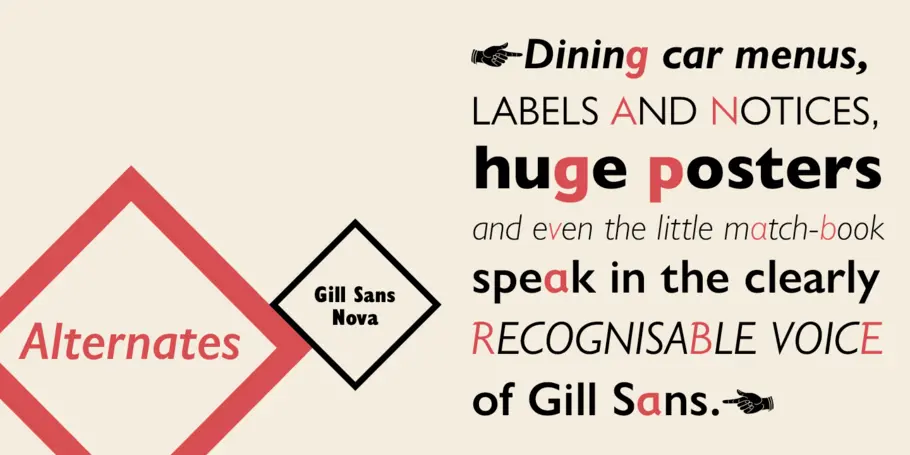
Gill Sans Nova®
La serie Eric Gill.
La serie Eric Gill es una colección de 77 fuentes de tres familias: Gill Sans® Nova, Joanna® Nova y Joanna Sans Nova. Todos los tipos de letra se inspiran en la obra original del influyente artista británico Eric Gill (1882-1940), consagrado escultor, grabador y diseñador de tipos. Nos encontramos ante tipos de letras digitales modernas, ya que incluyen una amplia gama de grosores, caracteres alternativos y compatibilidad con idiomas ampliada, pero que también rinden homenaje a los diseños originales de Gill.
El tipo de letra Gill Sans® Nova, obra del diseñador de Monotype Studio George Ryan, amplía la querida familia Gill Sans de 18 a 43 fuentes y presenta una gama coordinada de diseños romanos y comprimidos. Hay disponibles varias fuentes de visualización nuevas, incluido un conjunto de seis grosores con línea interna, fuentes de contorno sombreado que nunca se digitalizaron y Gill Sans Nova Deco, anteriormente retirada de la biblioteca Monotype.
Ofrece compatibilidad con varias características de OpenType®, lo que permite incluir caracteres experimentales de distintos momentos de la larga historia de Gill Sans, incluidas las diagonales puntiagudas de la «A», la «V» y la «W», y alternativas para la «b», la «d», la «p» y la «q». También se incorporan números proporcionales como alternativa a los diseños tabulares.
La familia Gill Sans Nova incluye un gran juego de caracteres que abarca las escrituras latina, griega y cirílica. Los grosores de visualización solo son compatibles con el alfabeto latino.
«Gill Sans fue capaz de tocar la fibra sensible del público tras su lanzamiento inicial, en 1928, y rápidamente ganó una gran popularidad», explica Ryan. «Se ha adaptado a todas las tecnologías de publicación, desde la composición tipográfica mecánica hasta la imagen digital y, en cada iteración, se le ha dado el mejor tratamiento por parte de Monotype. Esto queda especialmente patente con todos los elementos que hemos incorporado a la nueva serie, que conserva toda la esencia de Gill Sans. Mi objetivo era lograr claridad en todos los entornos digitales, añadir los grosores que faltaban y aportar más personalidad a la familia con nuevas fuentes de visualización, así como caracteres alternativos inspirados en Gill».
La familia de tipos de letra Gill Sans Nova forma parte de la nueva serie Eric Gill, que se inspira en el legado de Monotype para modernizar, ampliar y revitalizar la obra de Eric Gill, con más grosores, más caracteres y más idiomas. ¿El objetivo? Satisfacer una amplia gama de requisitos de diseño. La serie incorpora nuevos elementos inspirados en algunos de los trabajos no publicados de Gill (recientemente descubiertos en el archivo de dibujos de tipos de letra originales de Monotype), en cartas del diseñador y en documentos del siglo pasado.
Antes de iniciar su carrera profesional en la tipografía, George Ryan pasó tres años en el ejército estadounidense, sirviendo en Alemania y Vietnam. Fue uno de los grandes artífices de los primeros trabajos de desarrollo de herramientas de producción de fuentes digitales, y trabajó para Bitstream en los años ochenta y para Galapagos en los noventa. Según sus propias palabras, habría pasado más de 35 años «dibujando letras». Además, el diseñador cuenta con una amplia experiencia en programación de software y resolución de problemas de redes informáticas. Desde 2004, es diseñador de tipos en Monotype. Ryan diseñó el tipo de letra Oz Handicraft, basada en la obra de Oswald Cooper.